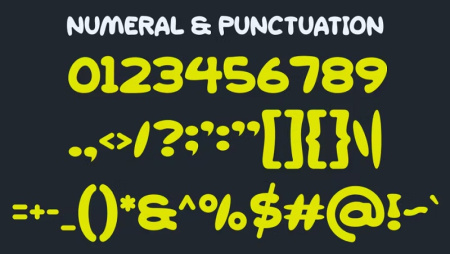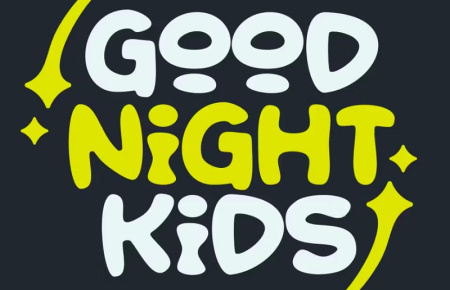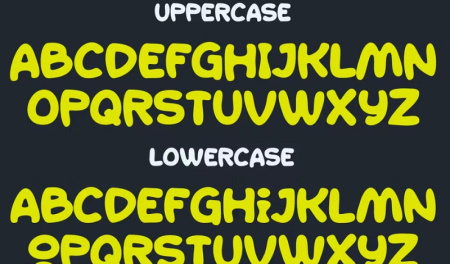
فونت انگلیسی Delion
فونت انگلیسی Delion یک فونت مدرن و زیبا است. این فونت برای هر پروژه برندسازی مانند لوگو، طراحی قالب، چاپ و بسیاری موارد دیگر مناسب است. شما می توانید در طراحی های مختلف از این فونت انگلیسی زیبا استفاده نمایید. برای مشاهده تصاویر این فونت مدرن و زیبا از جی اف ایکس دانلود در ادامه مطلب با ما همراه باشید.
فونت مدرن انگلیسی Delion
فونت انگلیسی مدرن Delion
✅ نام فونت انگلیسی: Delion
✅ حروف بزرگ
✅ حروف کوچک